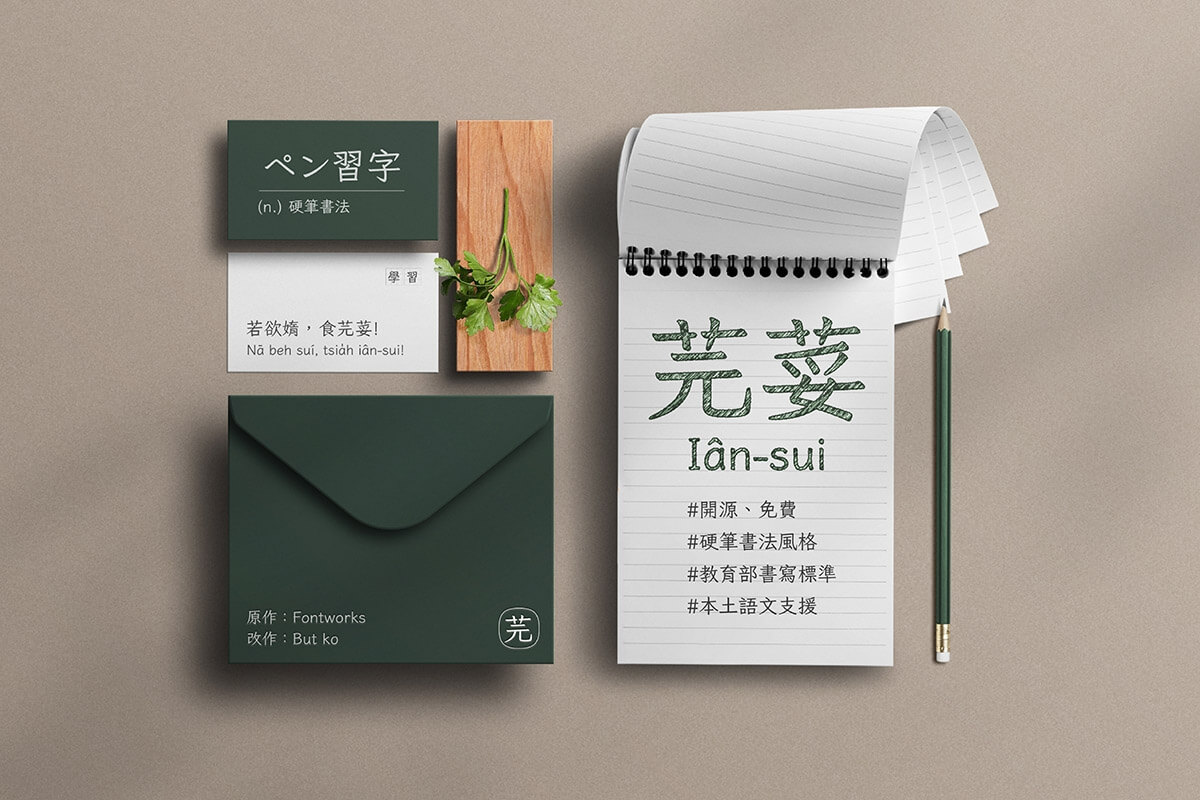
芫荽Iansui-Regular
芫荽 / iansui
- An open source Chinese font derived from Klee One (Fontworks).
- 基於 Fontworks 的 Klee One 衍生的開源繁體中文字型。
簡介
- Fontworks 的 Klee(クレー)字型原本內建於 macOS,因其兼具楷體筆調、又似仿宋整齊端正,具高易讀性與溫暖外形,廣受中文使用者喜好。然而畢竟是日文字型,雖然字數不少,但排中文時仍有一定程度缺字,一直是可惜之處。
- 但 2020 年底,Fontworks 忽然以開源授權釋出了 Klee One 字型,震驚字型圈。網路上已有許多其他專案嘗試為 Klee One 補上中文字,如簡體中文補字的 LXGW WenKai / 霞鹜文楷 與傳統字形補字的 Klee One 繁體中文版 等。
- 此專案「芫荽」則是嘗試盡可能調整字形貼近教育部標準字體,並補充台客語用字,貼近台灣需求,並適合學齡教育使用(如童書、國字習作等)。
- 由於原 Klee 的 Regular 偏細而預估使用需求較低,本專案以原 SemiBold 為底製作。
已涵蓋10310個臺灣常用漢字。